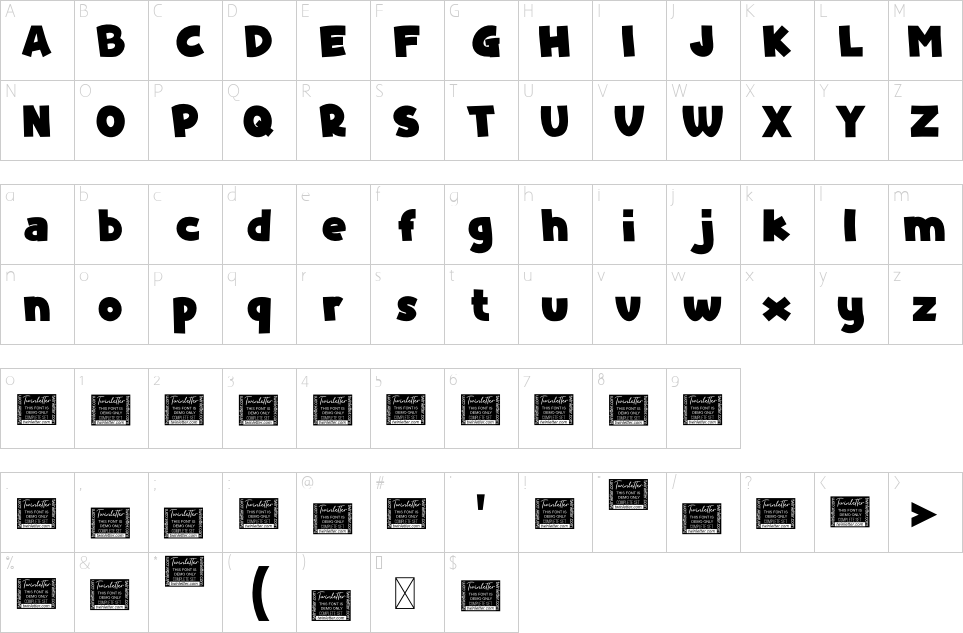
A fonte Ageer é uma elegante escolha para aqueles que buscam um estilo moderno e sofisticado para seus projetos de design gráfico. Desenvolvida por rozi, esta fonte vem em versões para Windows e Mac. Com um design cuidadosamente pensado, Ageer é uma excelente opção para aplicar um toque único em suas criações digitais. Seu download total ultrapassa as 1.882 vezes, o que prova o seu valor e popularidade. Seja você um designer de sites, um ilustrador digital ou simplesmente alguém que gosta de adicionar um toque de criatividade à sua designação, Ageer está aqui para ajudar você a expressar seus pensamentos de uma maneira que destaca a qualidade de seus trabalhos.